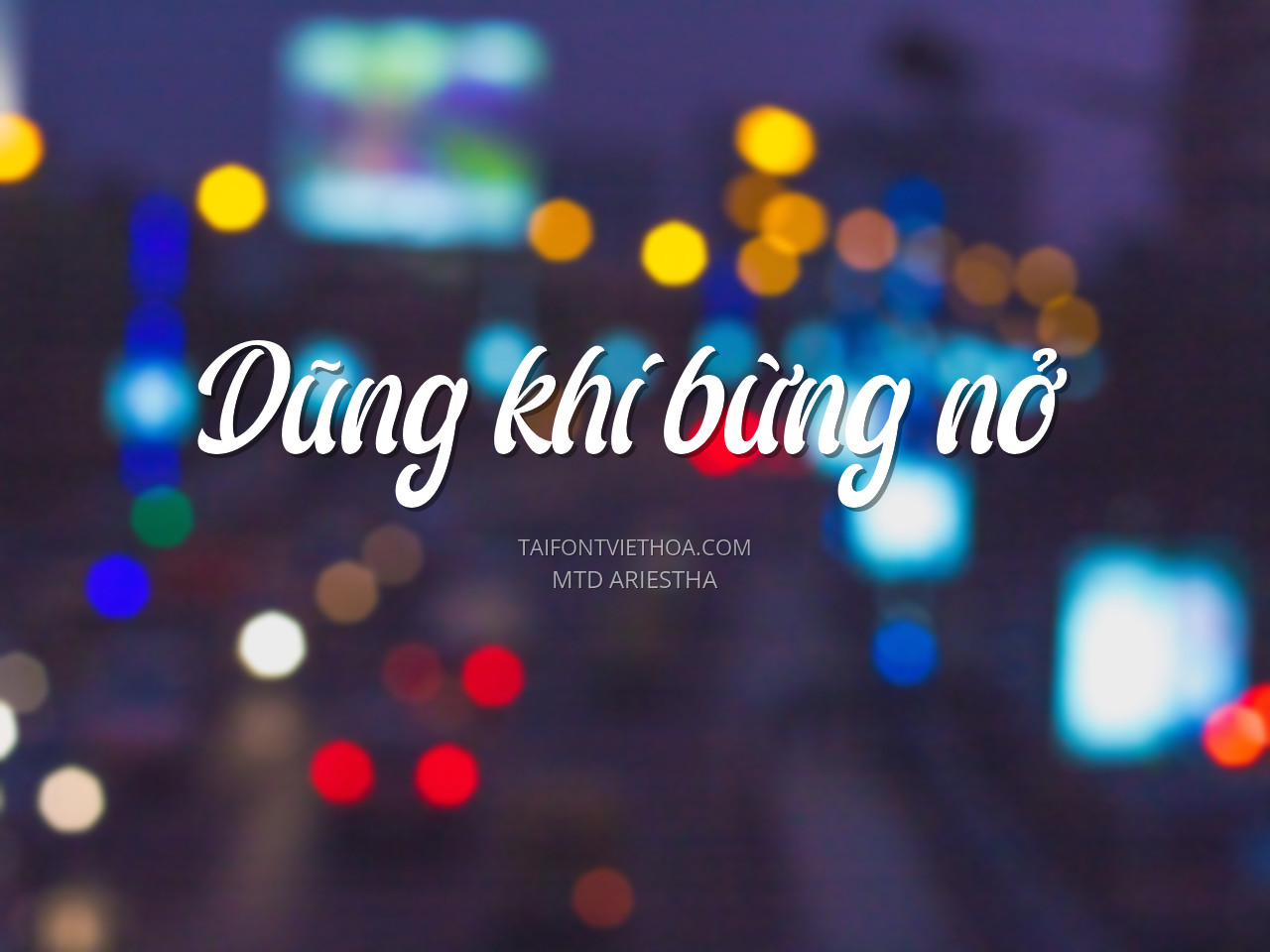
Font việt hóa MTD Ariestha
Giới thiệu về font Ariestha – Vẻ đẹp viết tay bay bổng, lãng mạn và đầy tính nghệ thuật
Ariestha là một font script viết tay hiện đại mang phong cách nhẹ nhàng, nữ tính và uyển chuyển. Font được thiết kế với các đường nét thanh mảnh, độ nghiêng vừa phải, mô phỏng nét chữ viết tay bằng bút lông mềm – mang lại cảm giác tự nhiên, dịu dàng nhưng vẫn rất cuốn hút. Với tính thẩm mỹ cao và độ bay bổng trong từng chữ, Ariestha là lựa chọn lý tưởng cho các thiết kế thương hiệu cá nhân, thiệp cưới, sản phẩm làm đẹp hoặc các thiết kế truyền cảm hứng.
Phiên bản Việt hóa do Mộc Hạthực hiện đã bổ sung đầy đủ dấu tiếng Việt và giữ nguyên tinh thần viết tay mềm mại của bản gốc. Taifontviethoa.comđã chọn lọc, sưu tầm và giới thiệu font Ariestha như một gợi ý hoàn hảo cho những ai tìm kiếm một kiểu chữ tinh tế, đầy tính nghệ thuật và gần gũi trong các thiết kế sáng tạo dành cho thị trường Việt Nam.
Đặc điểm thiết kế mềm mại và các ứng dụng lý tưởng của font Ariestha
Ariestha sở hữu form chữ nghiêng nhẹ, các nét thanh mảnh và uyển chuyển, nhiều ligatures và alternates giúp tăng độ linh hoạt trong bố cục và sáng tạo. Các ký tự swash cuối dòng cũng tạo điểm nhấn bay bổng, phù hợp cho các thiết kế giàu cảm xúc và nghệ thuật.
Font này rất phù hợp để sử dụng trong các dự án như: thiệp cưới, logo thương hiệu cá nhân, blog lifestyle, bao bì mỹ phẩm, thiết kế thời trang nữ, và trích dẫn truyền cảm hứng. Ngành nghề lý tưởng bao gồm: làm đẹp, thời trang, thiết kế thiệp cưới, handmade, wedding planner và các thương hiệu hướng đến sự nhẹ nhàng, nữ tính, nghệ thuật và sang trọng.